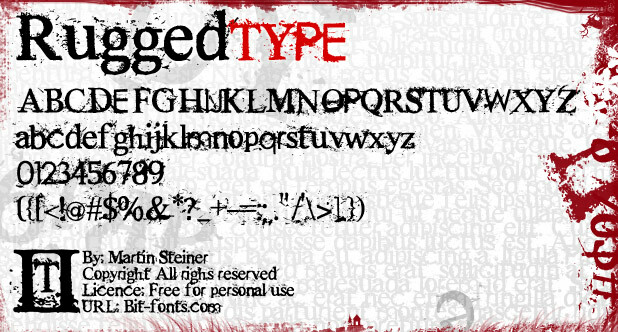
Rugged Type, eine kostenlose, distressed Serifenschrift von Steiner (Bit-Fonts), verleiht Ihren Schriftzügen einen rauen, abgenutzten Charakter. Mit ihren ausgefransten Kanten und feinen Flecken wirkt sie, als wäre sie mit hohem Druck gedruckt worden. Seit ihrer Veröffentlichung im Jahr 2008 verbindet sie robuste, klassische Formen mit einer unregelmäßigen Erosion, wodurch die Abnutzung wie eine konsistente Textur wirkt und nicht wie ein billiger Effekt.
Diese kostenlose Schrift passt perfekt zu Gig-Postern, Album-Covern, Zines, Skate-Grafiken, Verpackungs-Etiketten und redaktionellen Titelseiten, die einen authentischen, physischen Look erfordern. Sie funktioniert am besten in kurzen Schlagzeilen und Überschriften, wo die großzügigen Buchstaben genug Raum bieten, damit die feinen Einkerbungen und Details voll zur Geltung kommen.